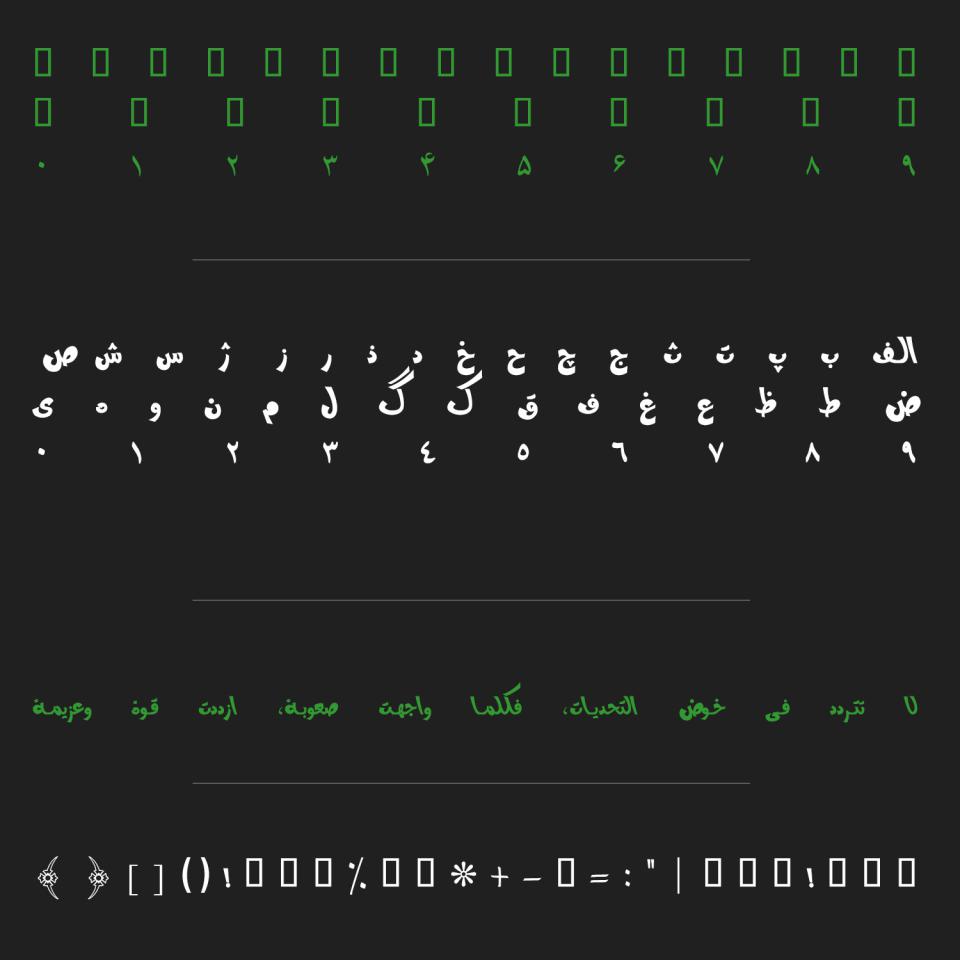
2 فونت وافی فارسی Wafi
فونت وافی فارسی، با ظاهری مدرن و خاص، می تواند جلوه ای متفاوت به نوشته های شما ببخشد. این فونت که از اصلاح و تغییر فونت عربی به فارسی شکل گرفته، ویژگی های منحصربه فردی دارد که آن را از سایر فونت ها متمایز می کند. یکی از ویژگی های برجسته آن، قد کشیده حروف است که به متن، ظاهری رسمی و خوانا می بخشد و در عین حال، گوشه های تیز حروف، حس پویایی و مدرن بودن را القا می کند.
این ترکیب، فونت وافی را برای استفاده در طراحی های گوناگون، از جمله عناوین، لوگوها، پوسترهای تبلیغاتی و حتی متون طولانی، مناسب می سازد. فرض کنید می خواهید برای یک رویداد مهم، پوستری طراحی کنید؛ فونت وافی با ظاهر جذاب خود، می تواند توجه مخاطب را جلب کرده و پیام شما را به شکلی مؤثر منتقل کند. یا در طراحی لوگو، این فونت با شخصیت قوی خود، می تواند به برند شما هویتی خاص ببخشد.
البته باید به این نکته هم توجه داشت که به دلیل همین ویژگی های خاص، ممکن است فونت وافی برای هر نوع متنی مناسب نباشد. برای مثال، در متونی با حجم بسیار زیاد و با موضوعات بسیار رسمی و سنتی، شاید فونت های کلاسیک تر انتخاب بهتری باشند. با این حال، اگر به دنبال فونتی هستید که هم خوانا باشد، هم مدرن و هم دارای شخصیتی قوی، فونت وافی می تواند گزینه ای ایده آل برای شما باشد. این فونت با ایجاد تعادل بین فرم و عملکرد، به نوشته های شما جان می بخشد و آن ها را از حالت معمولی خارج می کند. همچنین، این فونت به دلیل طراحی خاص خود، در موتورهای جستجو نیز به خوبی دیده می شود و می تواند به بهبود سئوی محتوای شما کمک کند.